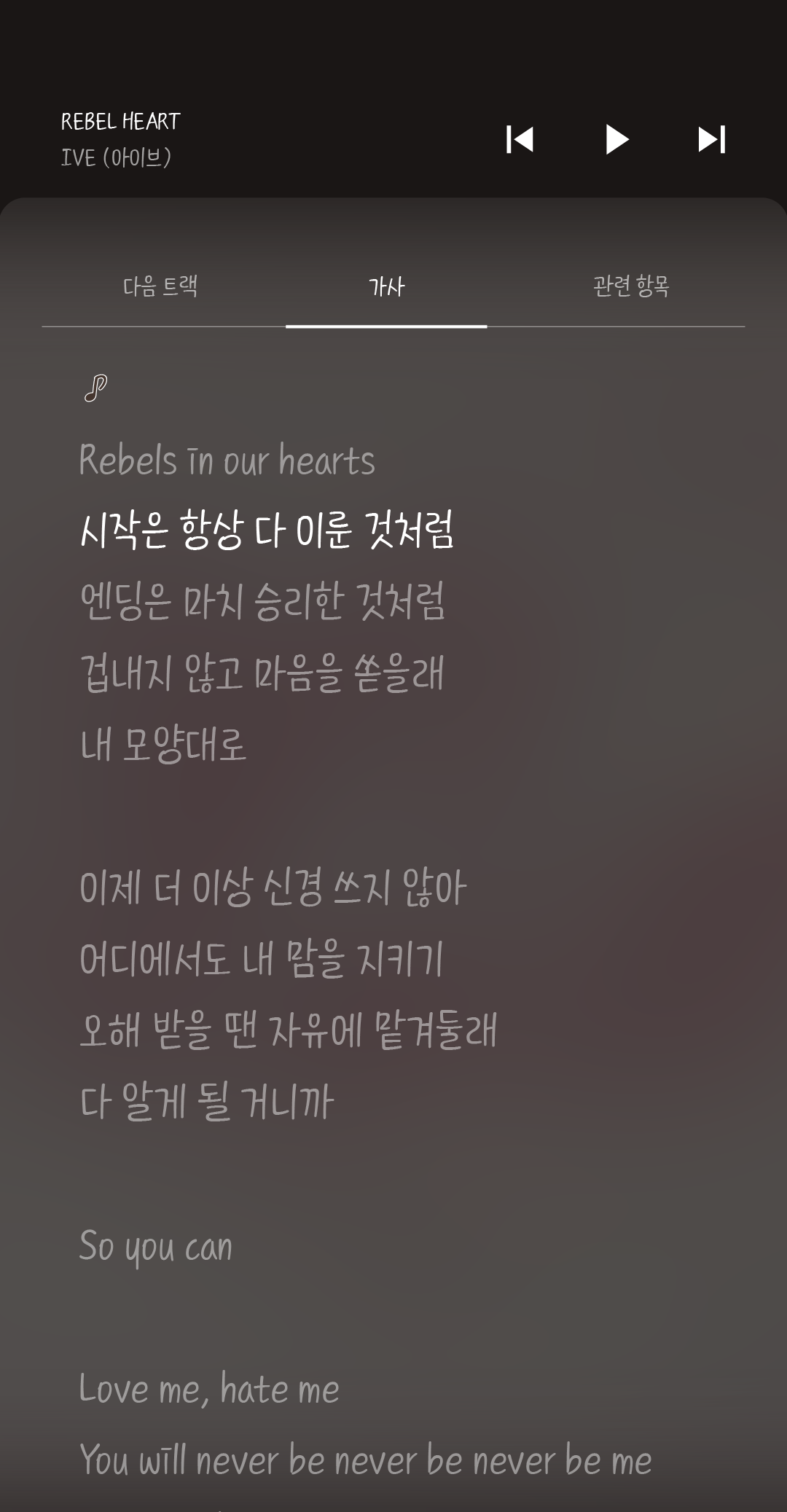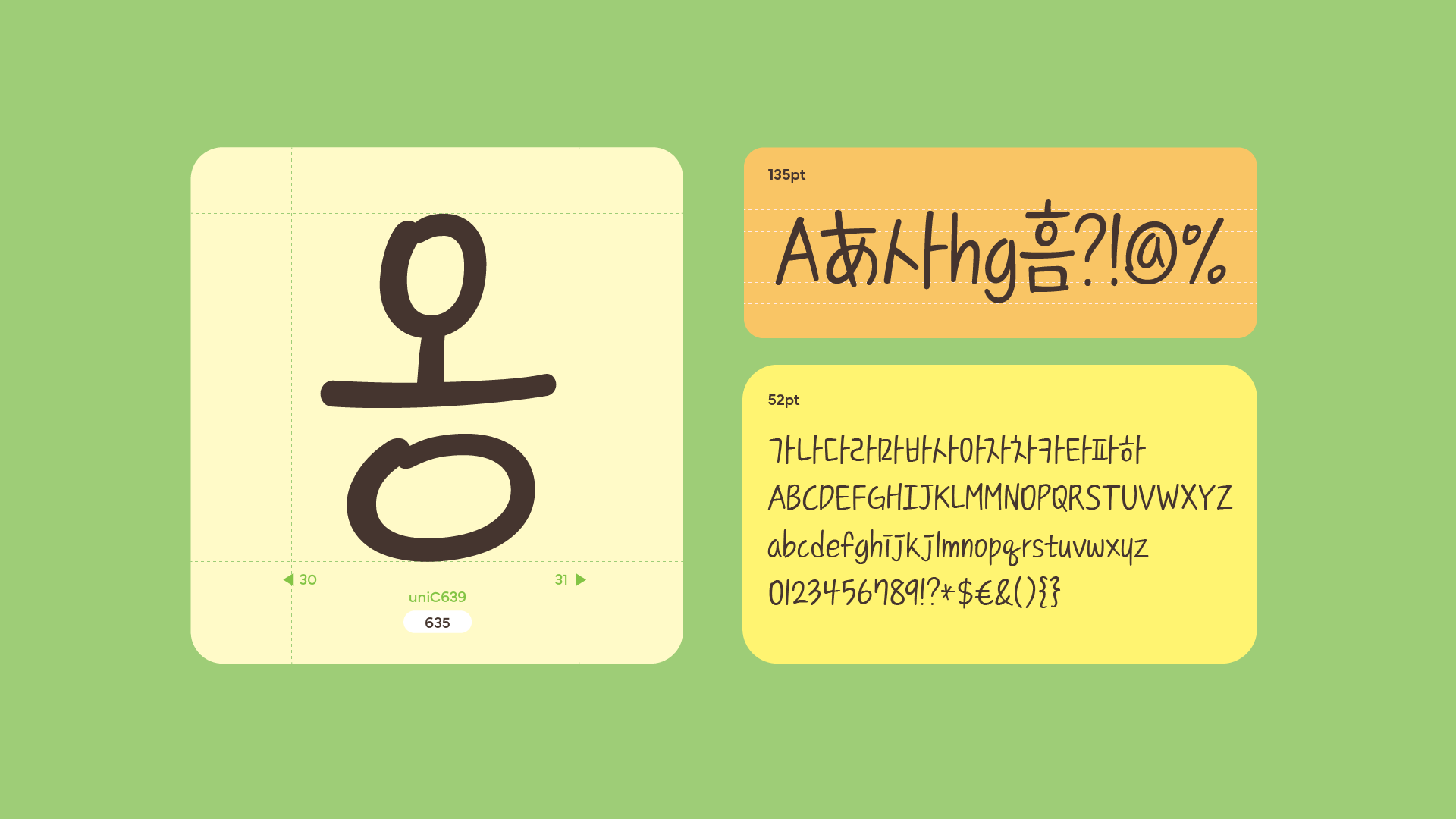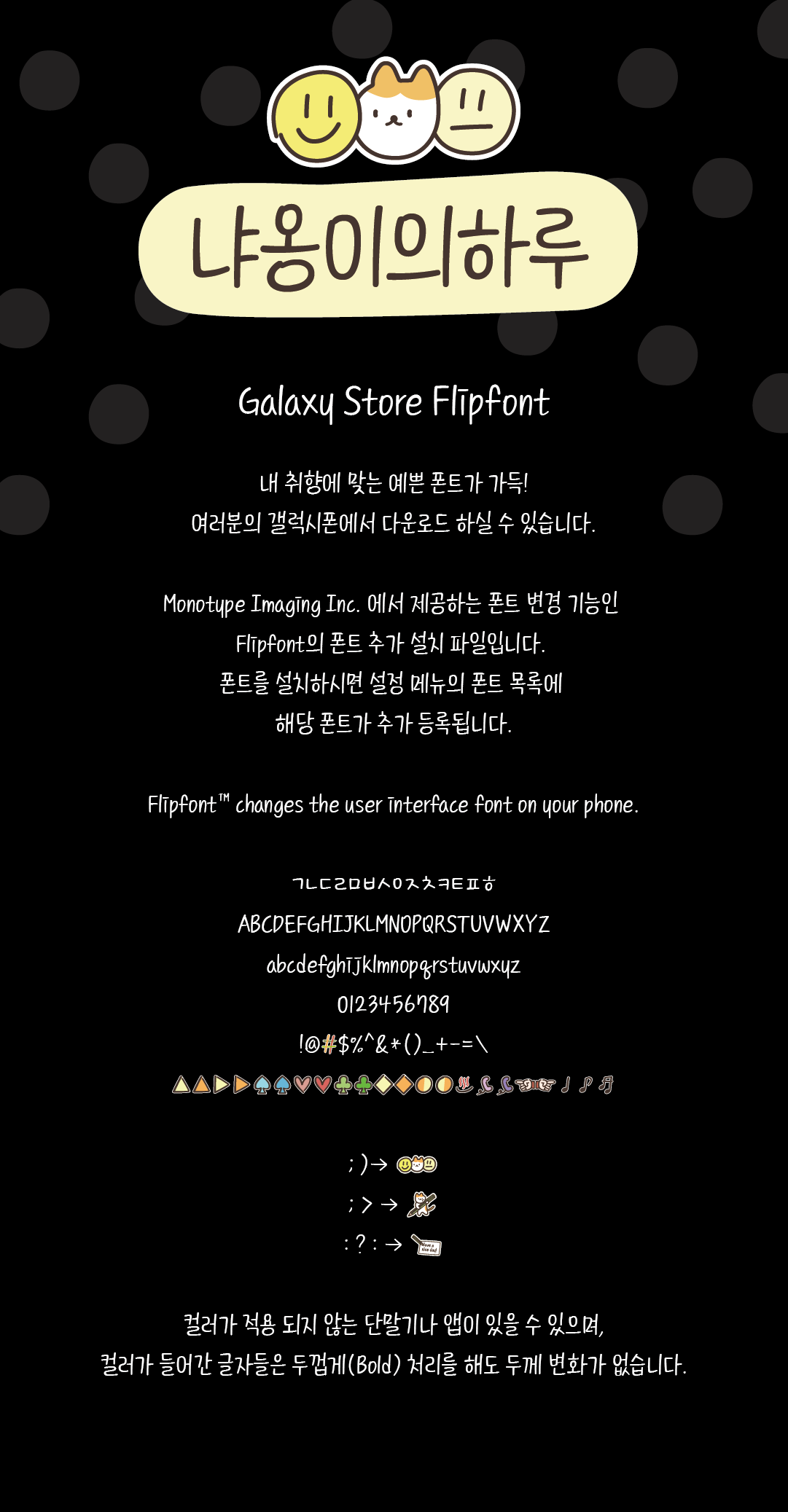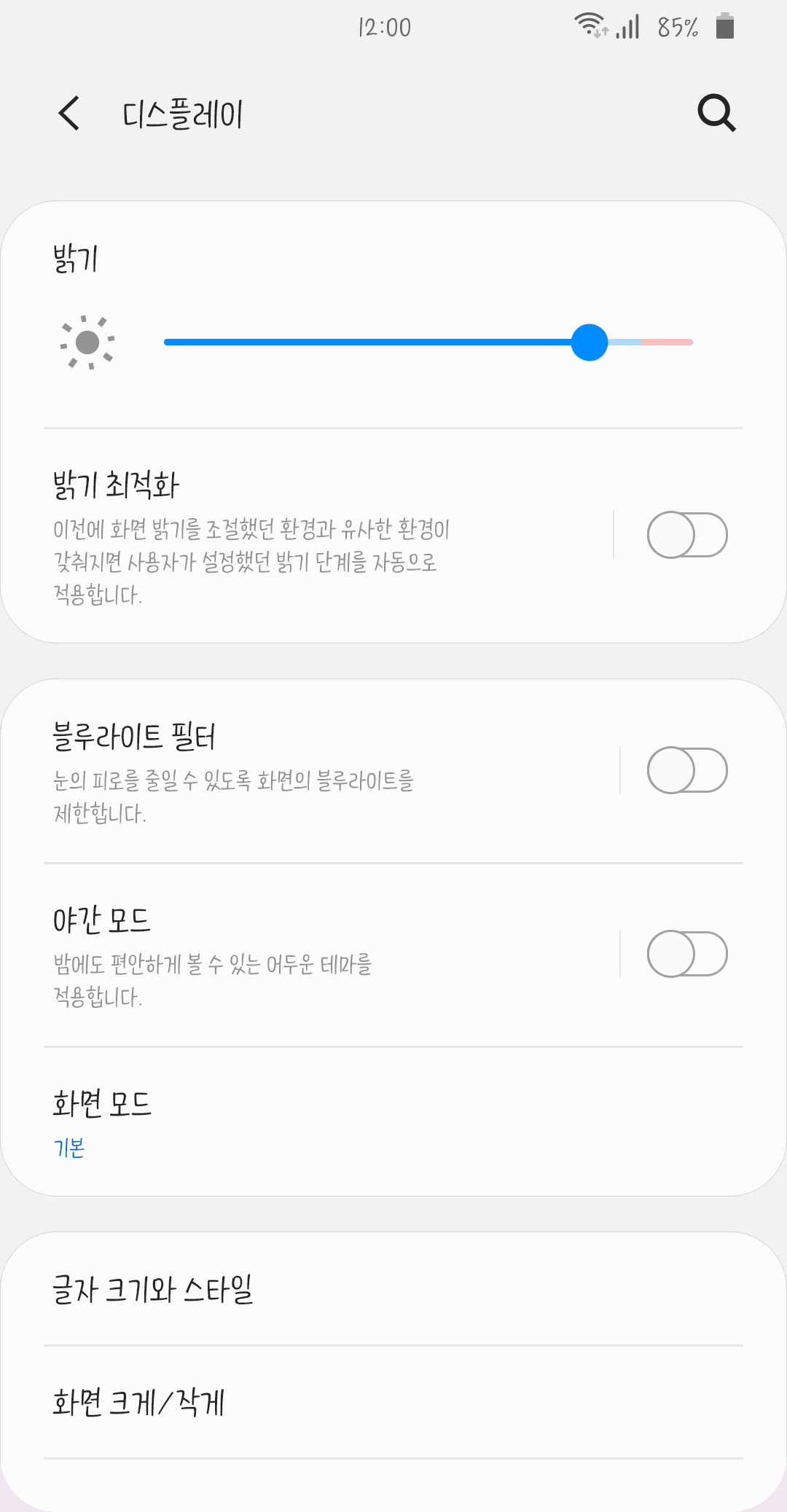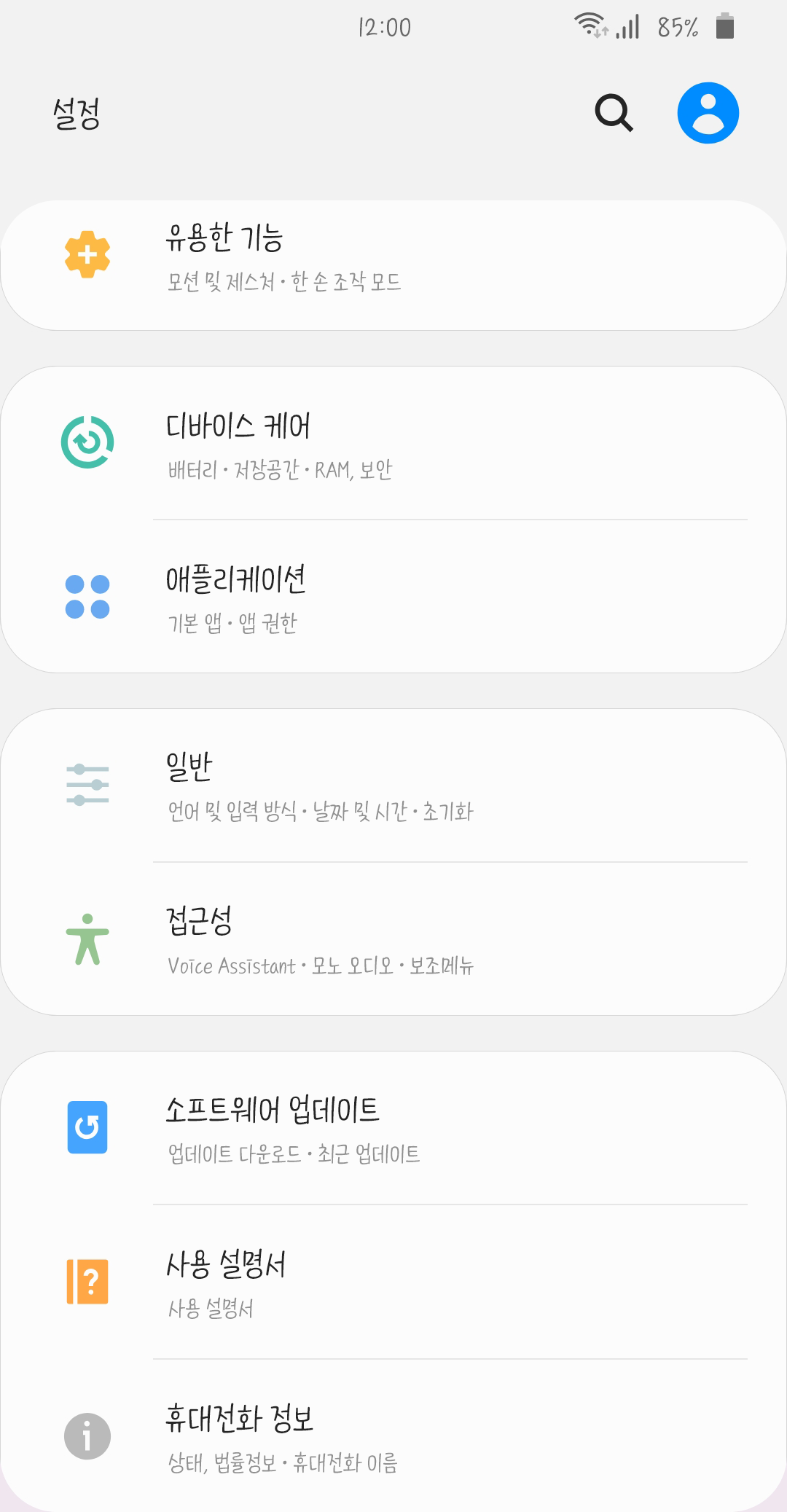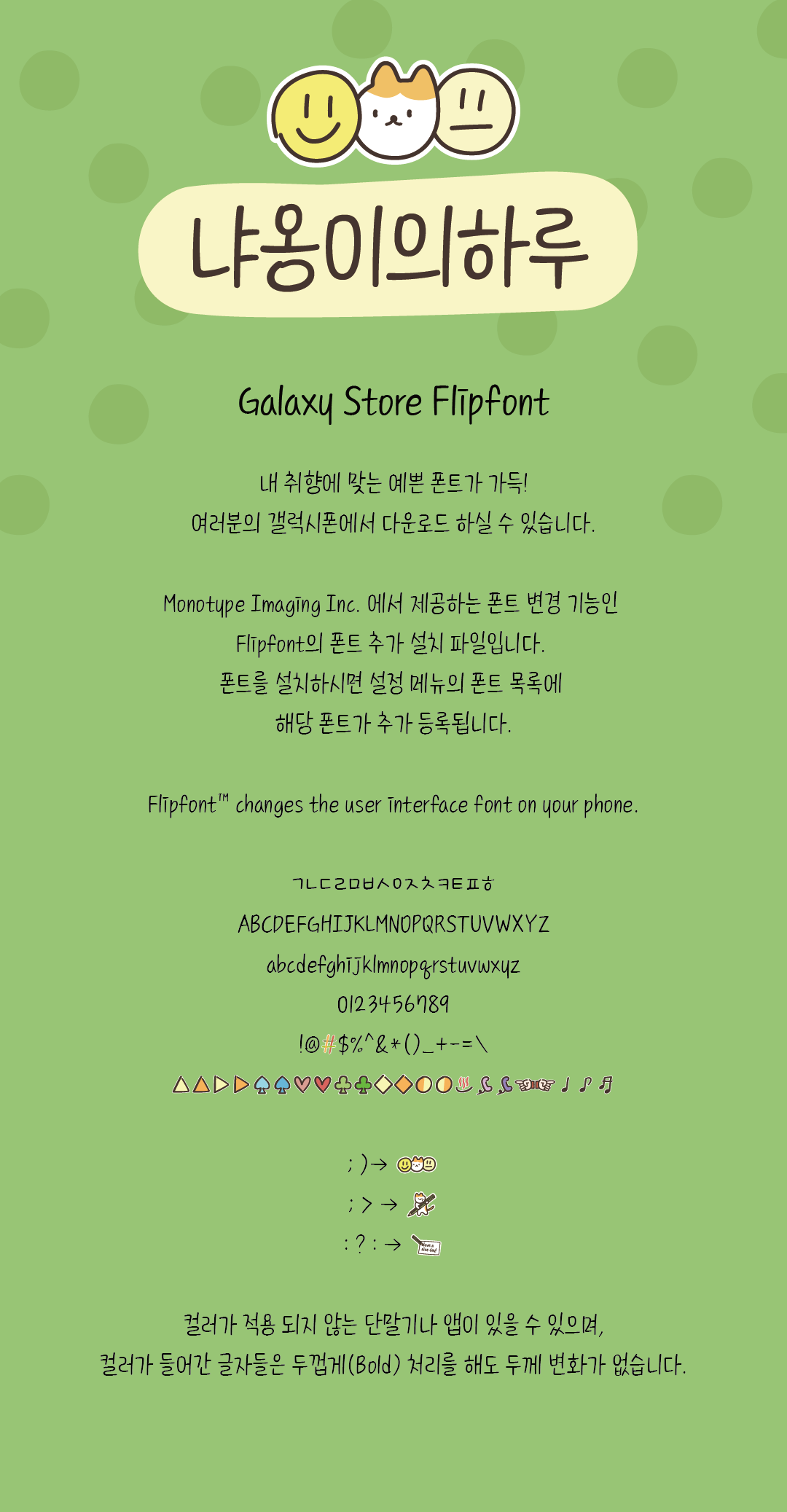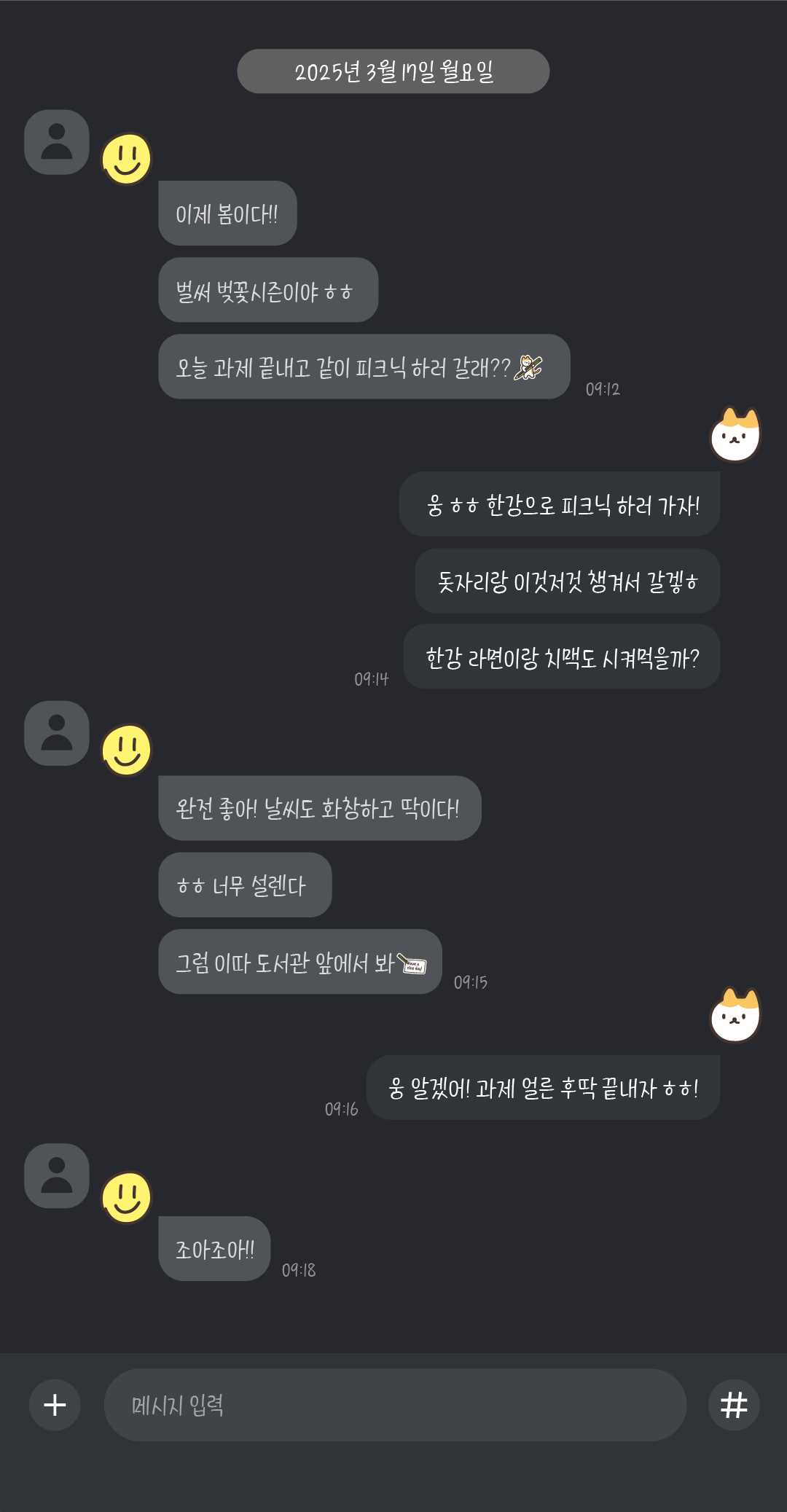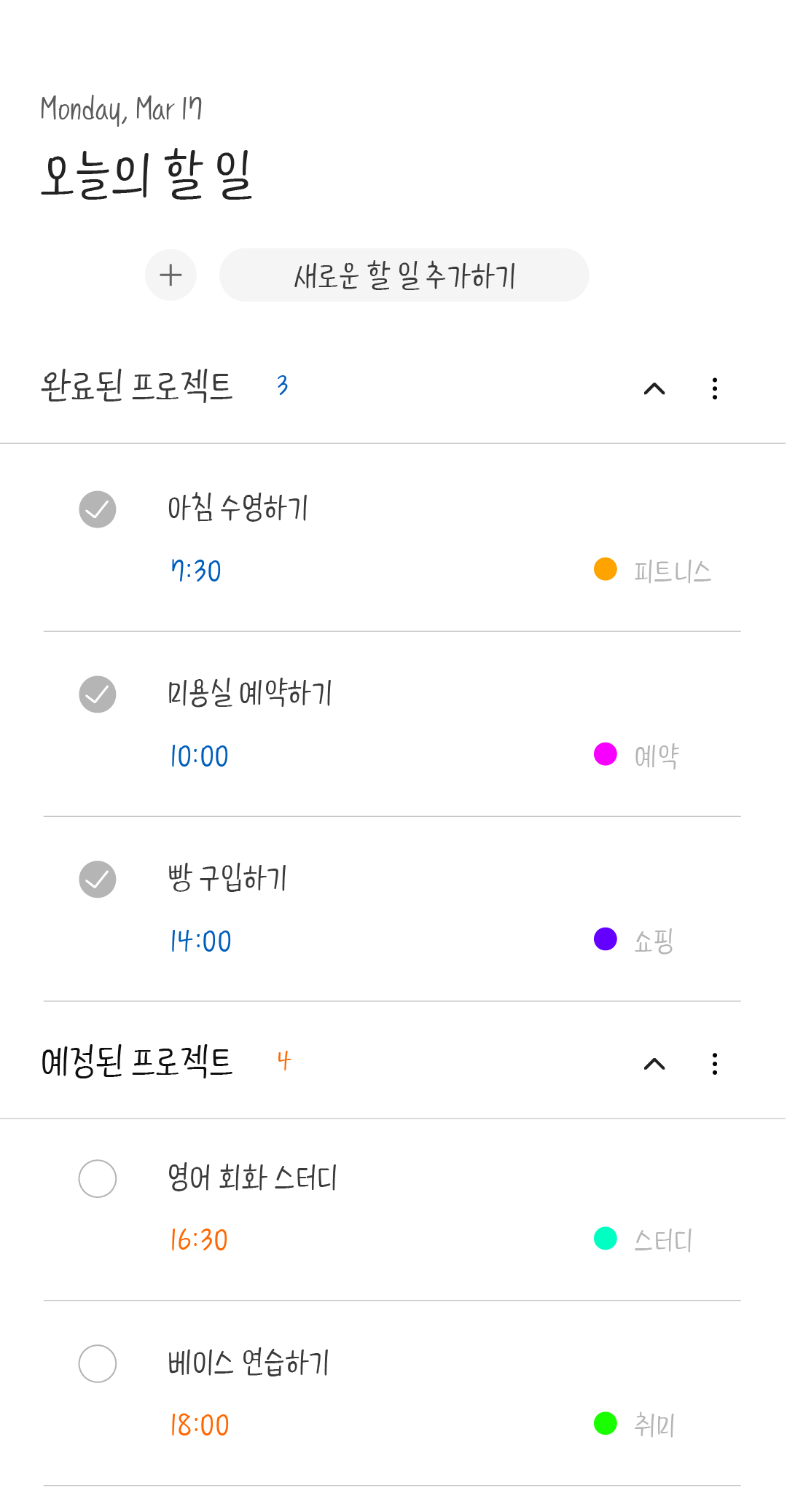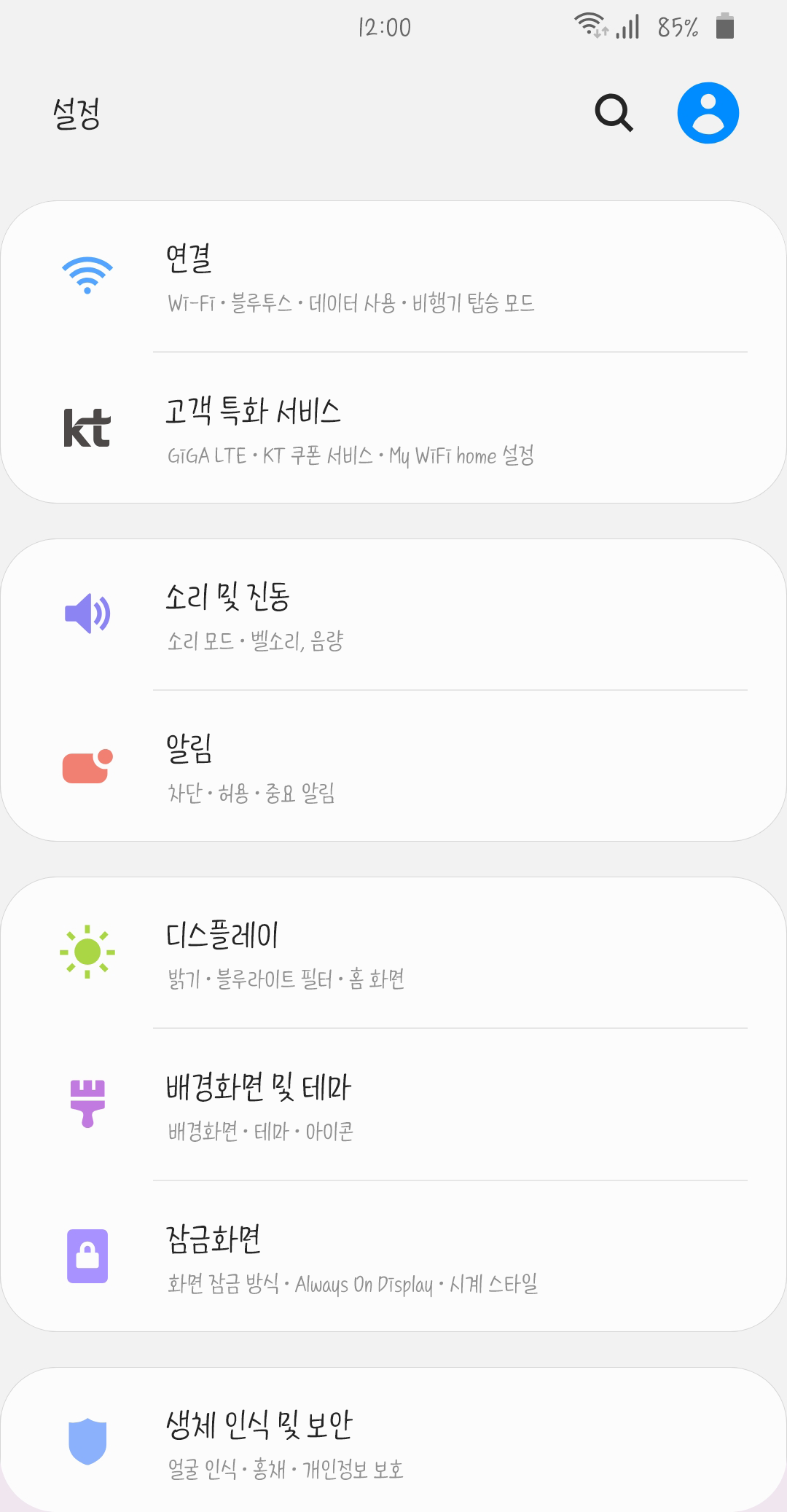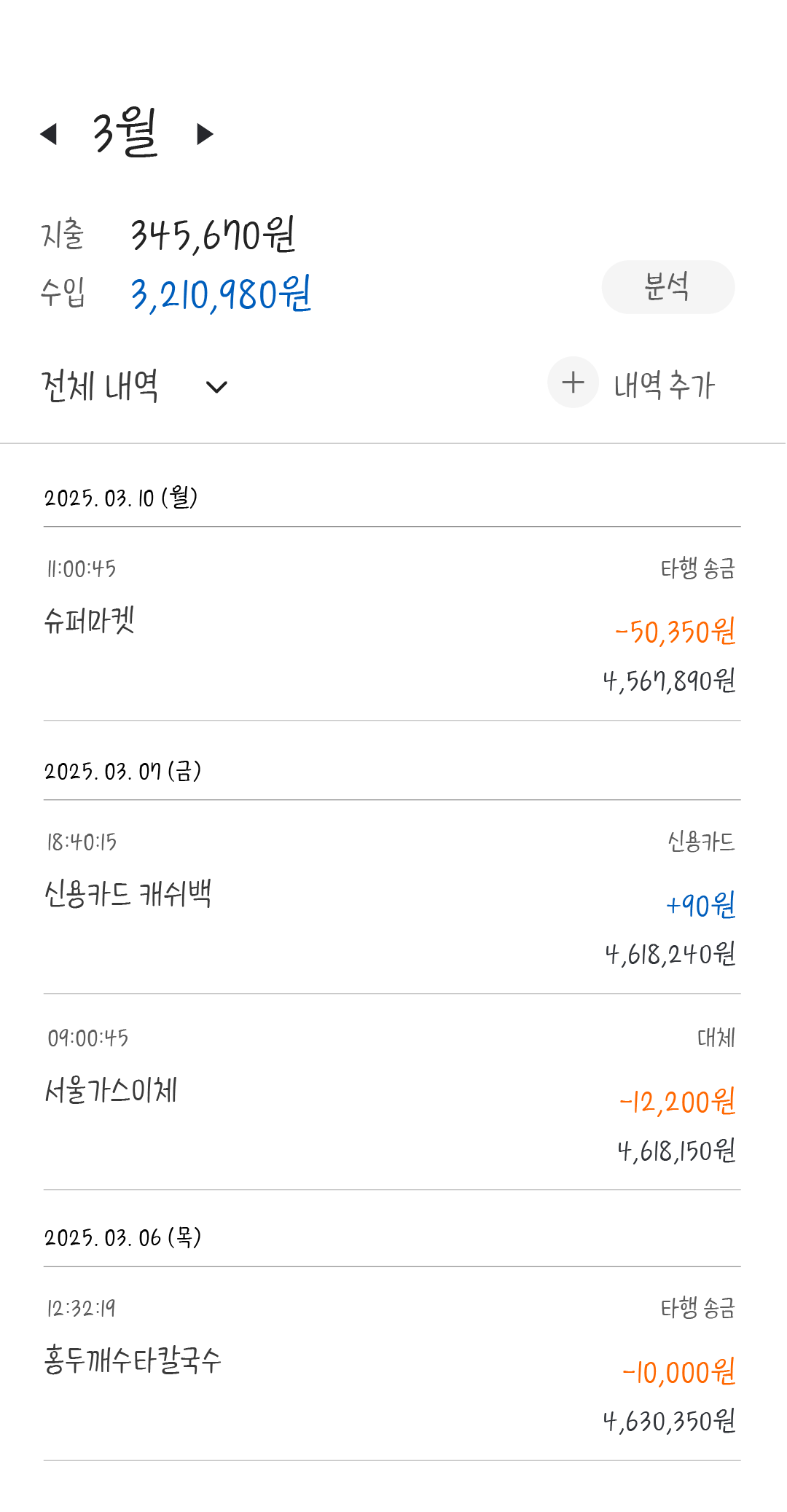
이 서체는 직접 쓴 손글씨를 바탕으로 제작된 서체입니다. 부드러운 필체의 가벼움과 넓은 받침의 무게감이 조화를 이루어 안정감을 줍니다. '냐옹이의 하루'라는 이름처럼 밝고 따뜻한 분위기가 느껴지는 서체입니다.
이 서체는 직접 쓴 손글씨를 바탕으로 제작한 서체입니다. 부드러운 필체의 가벼움과 넓은 받침의 무게감이 조화를 이루어 안정감을 줍니다.
'냐옹이의 하루'라는 이름처럼 밝고 따뜻한 분위기가 느껴지는 서체입니다.
TE 냐옹이의하루